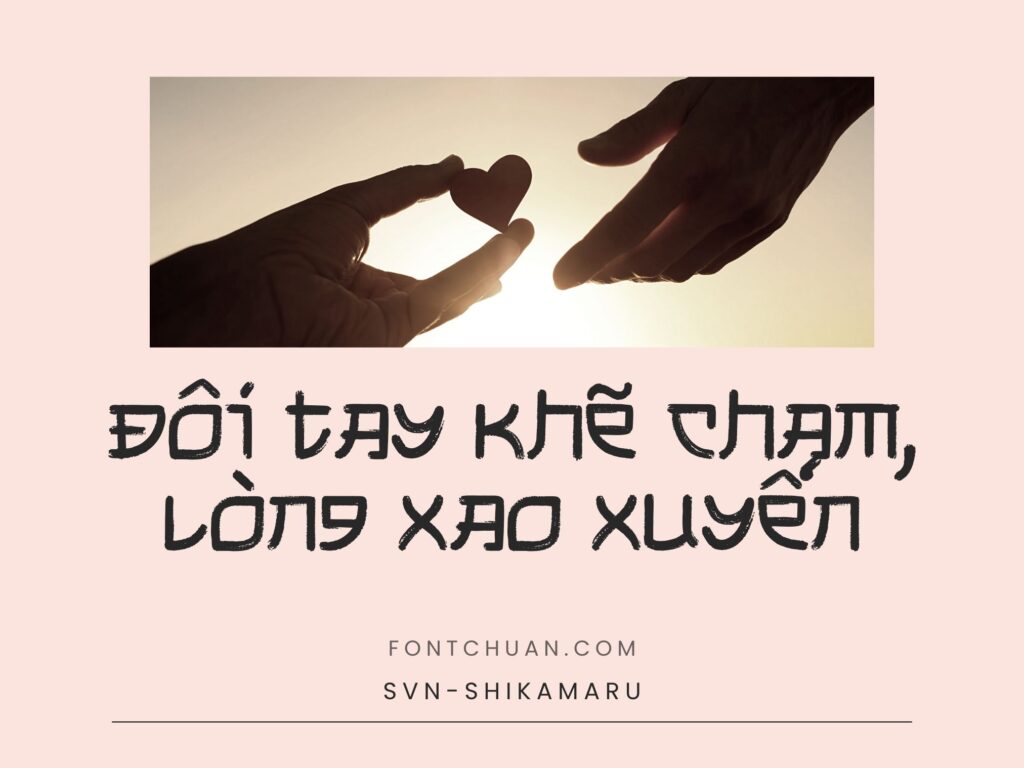
Font SVN Shikamaru Việt Hóa
Tác giả Font: Ahmad Ramzi Fahruddin
Font SVN Shikamaru là phiên bản Việt hóa của kiểu chữ Shikamaru, được thực hiện bởi STYLEno.1 Fonts. Shikamaru là một kiểu chữ mang phong cách Nhật Bản, được thiết kế với các nét vẽ thô tối giản, lấy cảm hứng từ chữ Kanji. Font này là kiểu chữ in hoa, với sự khác biệt giữa chữ hoa và chữ thường, tạo nên sự đa dạng trong thiết kế. Shikamaru phù hợp cho các dự án yêu cầu phong cách Á Đông hoặc Nhật Bản, như thiết kế logo, tiêu đề, bao bì sản phẩm và các ấn phẩm truyền thông. ([STYLEno.1 Fonts](https://www.svnfont.com/viet-hoa-svn-shikamaru/))
SVN Shikamaru lý tưởng cho các dự án thiết kế yêu cầu sự độc đáo và mang đậm phong cách Nhật Bản, như thiết kế logo, tiêu đề, bao bì sản phẩm và các ấn phẩm truyền thông. Các ngành nghề như quảng cáo, giáo dục và công nghệ có thể tận dụng font này để tạo điểm nhấn trong thiết kế. Ngoài ra, font cũng thích hợp cho các sự kiện như Tết, Giáng sinh, Halloween và các lễ hội khác.